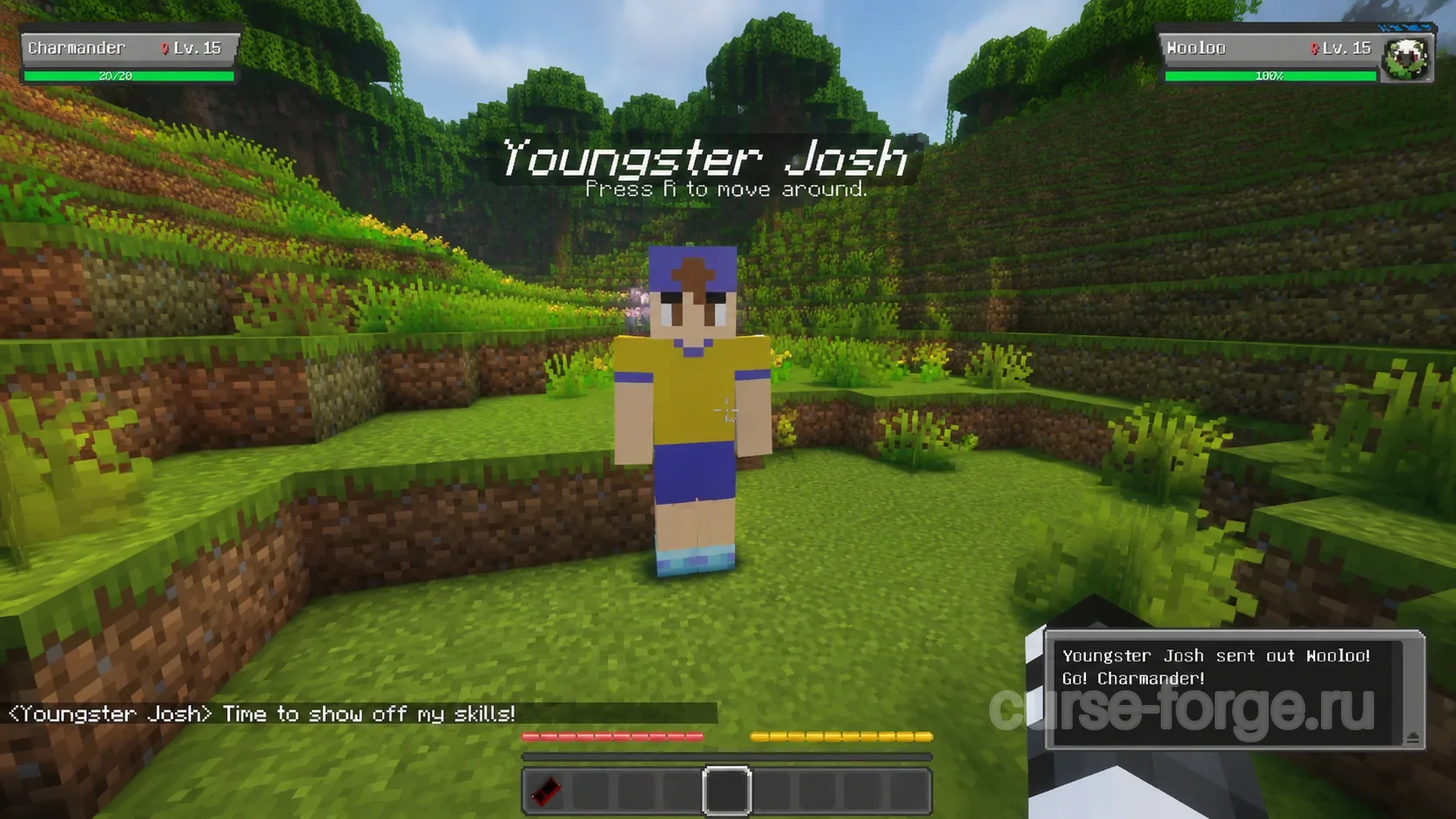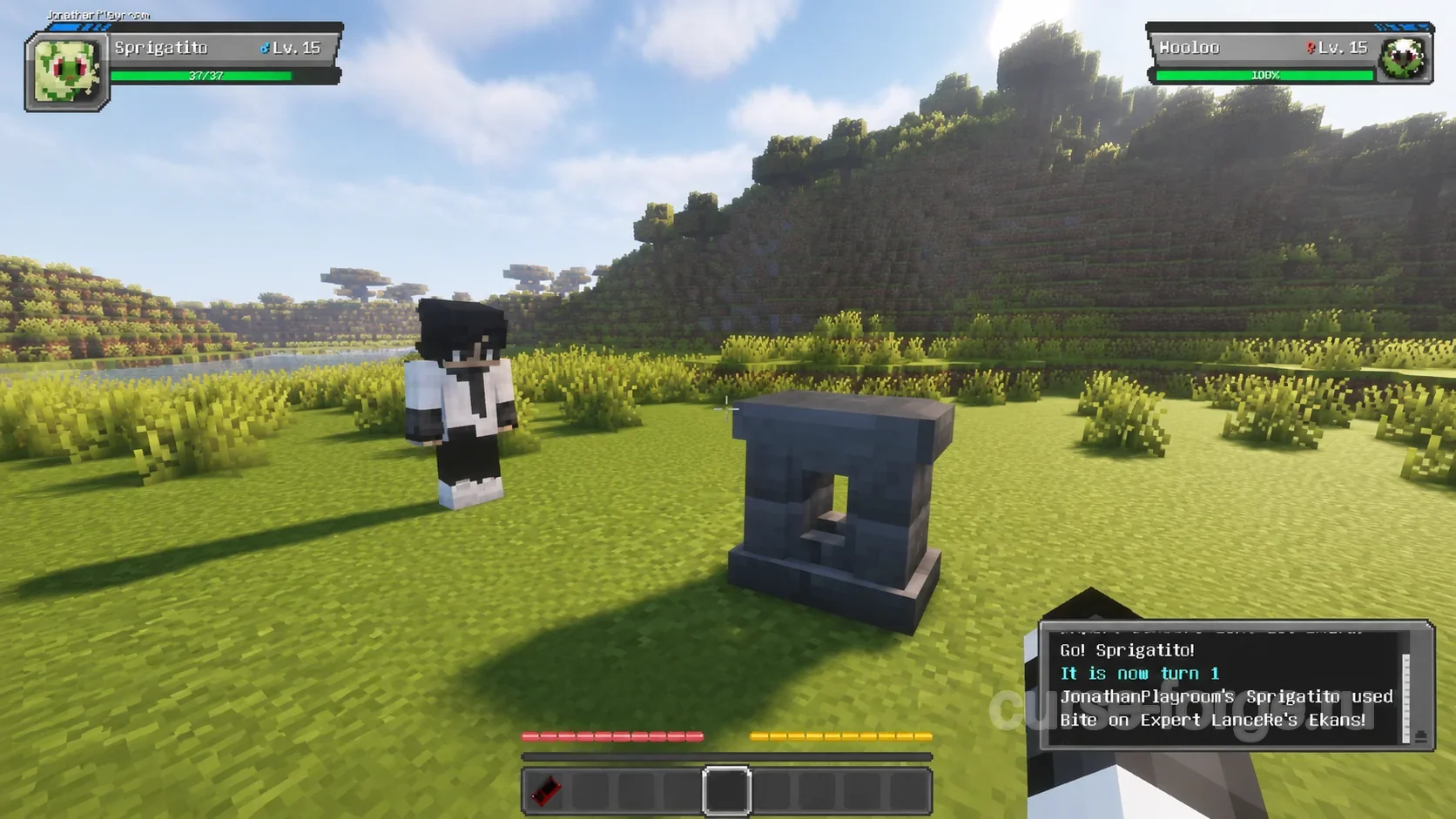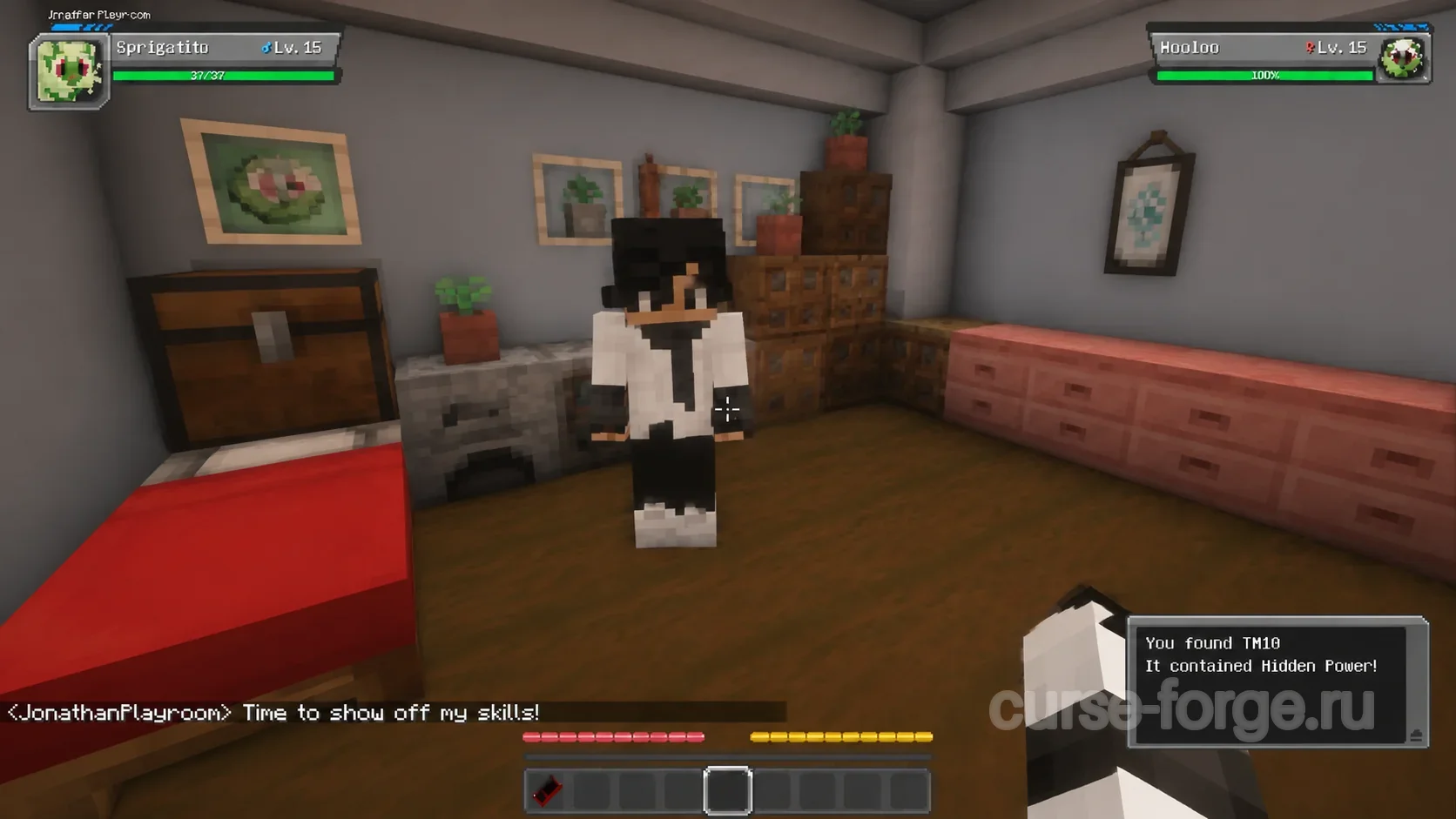
Minecraft Font Addon — простой, но крутой ресурс-пак, который меняет стандартный тонкий шрифт Minecraft на более жирный и читаемый вариант, идеально подходящий для кириллицы и других языков. Если ты устал squint’ить на меню, чаты и таблички, этот мод добавит четкости и стиля твоему игровому интерфейсу.